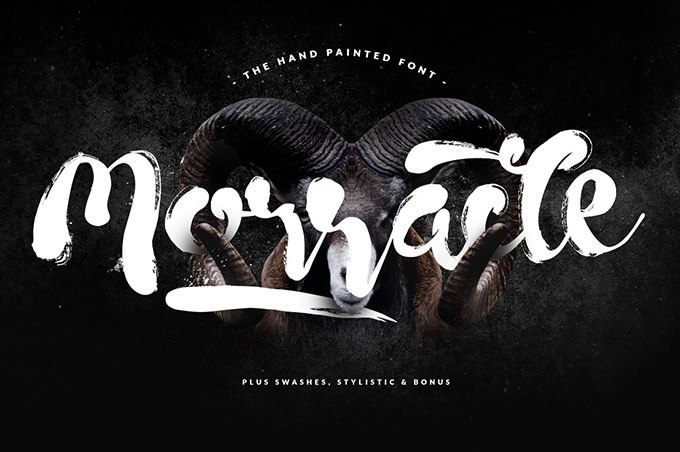
Шрифт Morracle (Латиница)
Автор: Maulana Creative
Представляем вам потрясающий рукописный шрифт, вдохновленный чернильным письмом. Шрифт содержит в себе много различных знаков и может служить отличным украшением к вашим новым проектам.